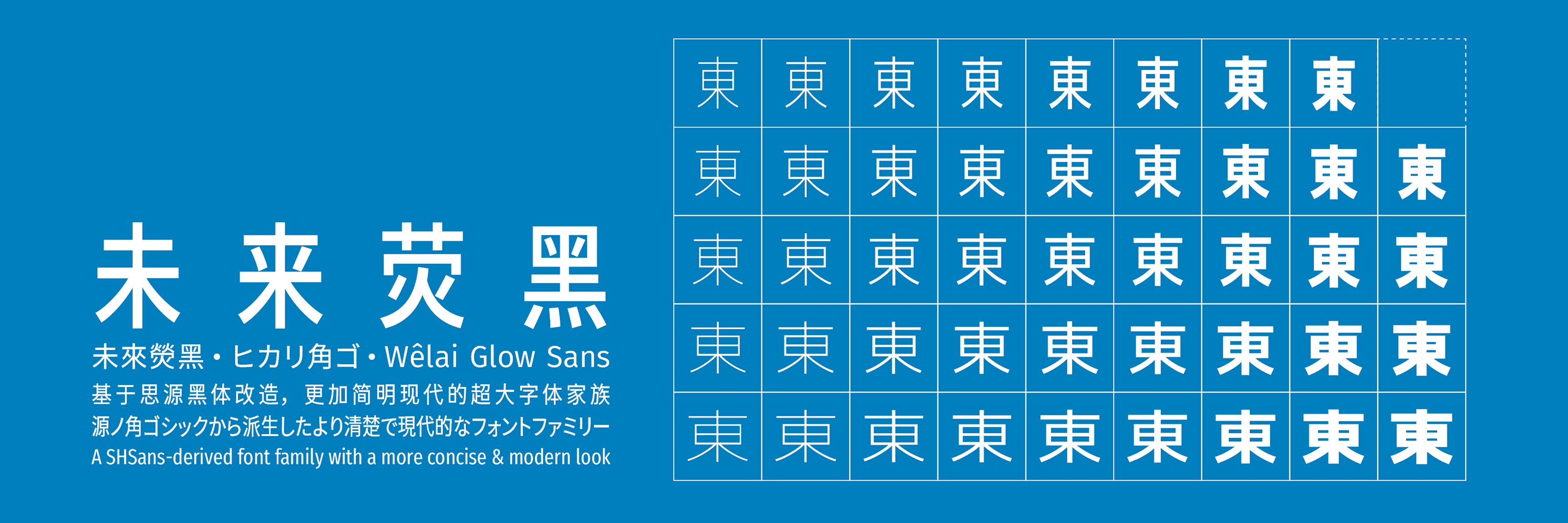
未来荧黑
别称:Glow Sans / 未來熒黑
未来荧黑·未來熒黑·ヒカリ角ゴ·Wêlai Glow Sans
未来荧黑是一个基于思源黑体、Fira Sans 和 Raleway 的开源字体项目,支持简体中文、繁体中文与日文;思源黑体的 7 字重被扩展为 9 字重,并提供了宽度系列,全家族共 44 款字体。
相比于思源黑体,未来荧黑的造型更加简明现代,版面效果清新轻快。未来荧黑的中宫与字面更加收敛,重心在字重之间经过了重新配置;笔画细节上处理得更加干净,简洁而平直化。您可以下载样张来预览未来荧黑的设计。
未来荧黑的实现介于参数化与轮廓滤镜,使用了图像处理算法对字形建模。字体的制作并没有借助字体设计软件,而是用一个 Web 实现的可视化调参工具来确定字体参数。